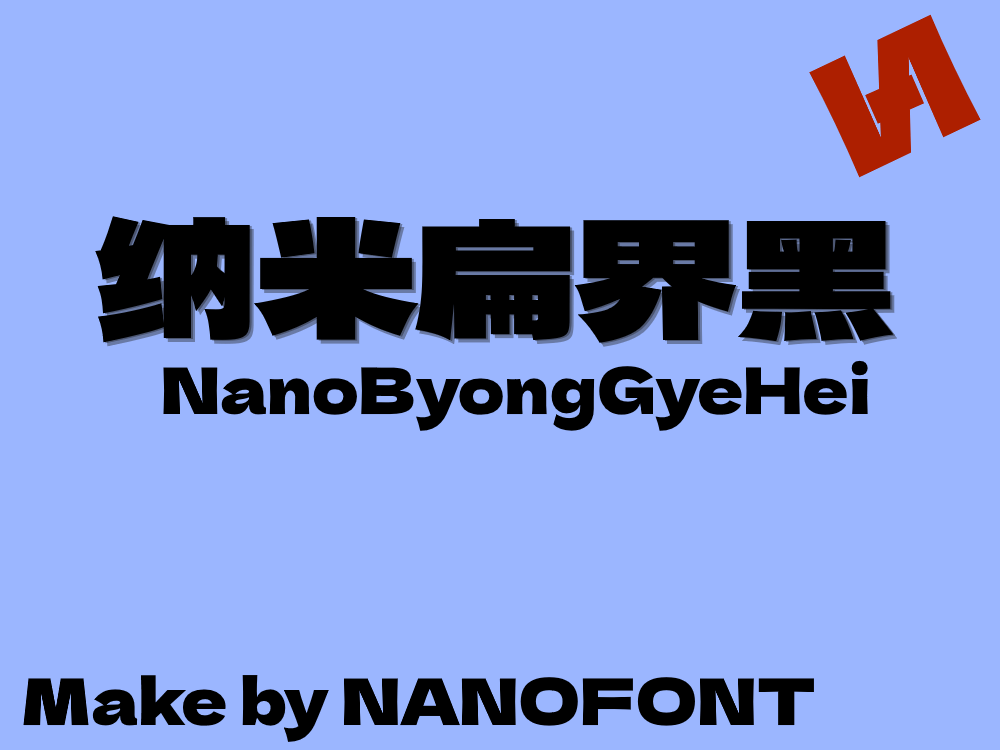
蓝色背景,右上角有红色标志,中间展示黑色粗体字“纳米扁界黑”及英文“NanoByongGyeHei”,底部标注“Make by NANOFONT”。-刊刻Kntuk
纳米扁界黑 NanoByongGyeHei 这款字体,是在标小智无界黑的整体骨架上重新整理出来的。设计上把馒头黑那种熟悉的笔画习惯也融了进去,让字的结构和节奏更顺手。原先字库里没完全排满的地方,还有好些零散的空缺细节,这次都是一一对着原稿慢慢补齐的。等两边的基础底子彻底对接好之后,那些原本容易遗漏的小部件也就顺着结构自然补全了,整套字稿算是从头到尾完整地走通一遍。
制作者:H.S.S. – 寒沙